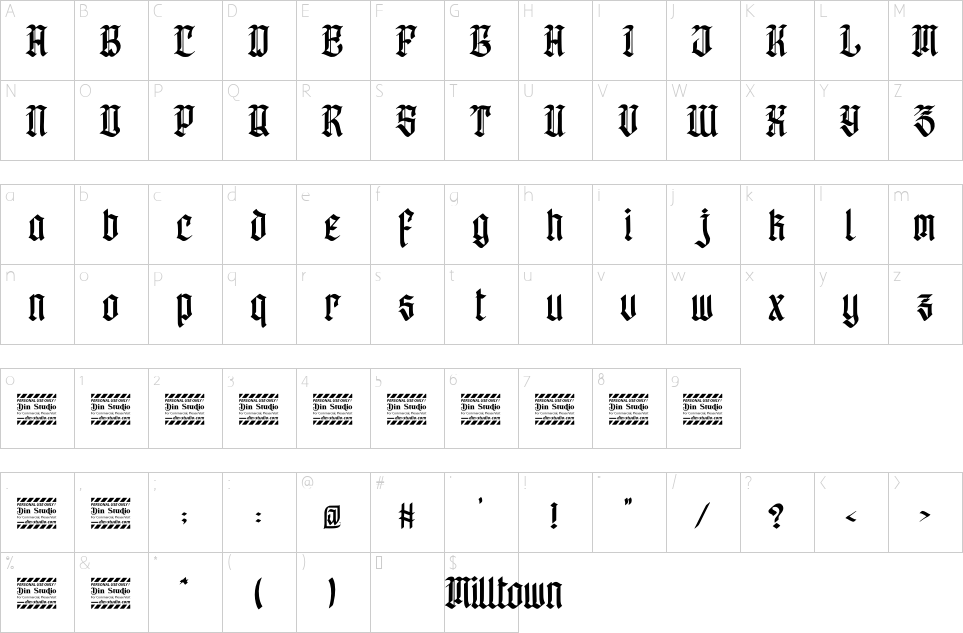
A fonte Milltown é uma criação de Din Studio que adiciona um toque suave e aconchegante a qualquer projeto de design. Esta fonte, disponível para Windows e Mac, foi projetada para oferecer um equilíbrio entre elegância e conforto, tornando-a ideal para aplicações em design editorial, gráficos em vetor ou até mesmo em design gráfico. Com 1.678 downloads, a Milltown é uma opção sólida e confiável para designers gráficos que desejam adicionar um toque pessoal à sua produção. Seja para criar um logotipo atraente, reformatar uma imagem ou criar um layout de e-mail, a Milltown é uma escolha sólida para qualquer projeto. Com seu design suave e versátil, a fonte Milltown é uma excelente opção para quem procura uma fonte gratuita que se destaca.